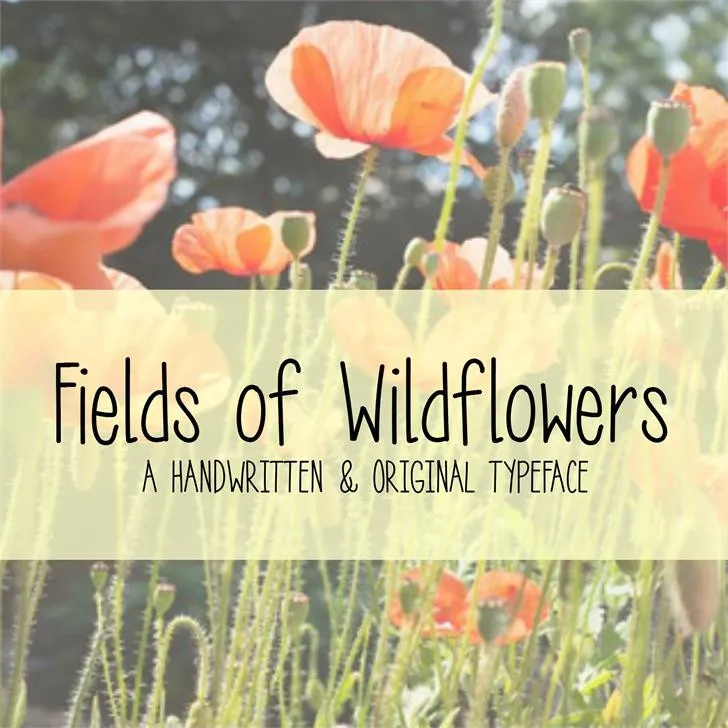
A ‘MRF Fields of Wildflowers Font’ é uma fonte escrita à mão criada pelo designer Hamilton, perfeita para quem procura estilo natural e envolvente para aplicar em projetos pessoais ou pequenos negócios. Inspirada nos campos floridos da natureza, essa fonte possui linhas levemente desenhadas que remetem à delicadeza das flores selvagens, com um toque suave e fluido que certamente vai deixar seu design mais autêntico e charmoso. Perfeita para criações personalizadas, scrapbooking ou até mesmo aplicativos de mensagens, a ‘MRF Fields of Wildflowers Font’ oferece o suficiente para qualquer projeto. Ela suaviza o texto com uma elegância que ressoa com o universo dos campos floridos, fazendo da sua utilização não apenas um ato de design, mas também uma conexão mais profunda entre os designs criados e o ambiente natural ao nosso redor. Além disso, é importante lembrar que esta fonte está disponível gratuitamente para uso pessoal. Para comercialização ou a inclusão em produtos vendidos, é preciso adquirir um licença. Visite www.monkeyroodlesfonts.com para mais detalhes e informações sobre o processo de compra.